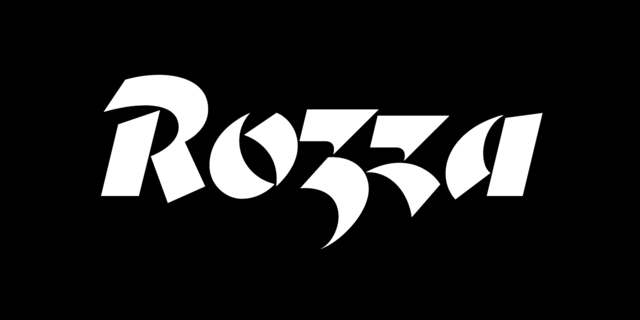
Rozza – це трафаретний курсивний наджирний шрифт для екстремальної акциденції. Дивлячись на ці літери легко згадати історію про красуню та чудовисько, що цілком зрозуміло. З одного боку шрифт страшний і небезпечний, а з іншого – в ньому пульсує краса і пристрасть. Спробуйте поєднати Rozza з Displace, вийде прекрасна шрифтовая пара. Шрифт розробив Денис Серебряков у 2017 році.